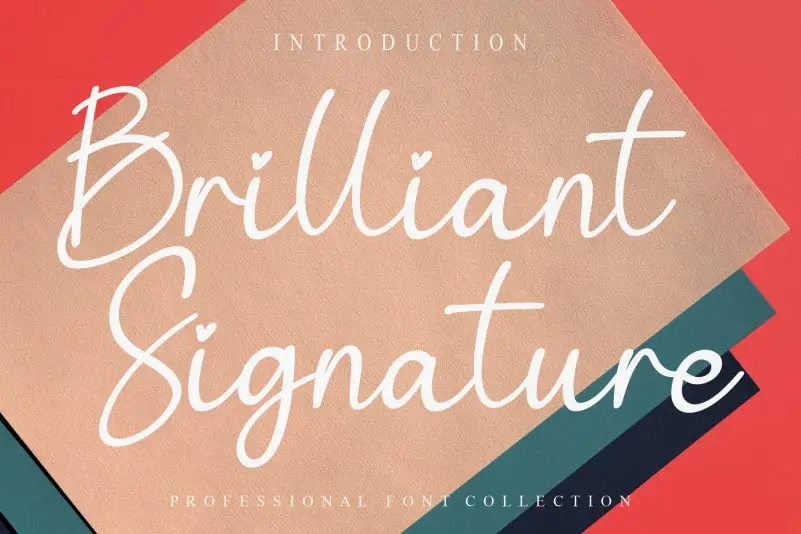
Brilliant Signature Script Font – Download Grátis
Aqui está uma descrição em português do Brasil para a página de download da fonte ‘Brilliant Signature Script Font’, mantendo o tom informativo e convidativo: Descubra uma experiência única com a fonte ‘Brilliant Signature Script Font’. Especialmente criada para quem valoriza personalidade, essa fonte é perfeita para criar mensagens de impacto. Sua elegância e delicadeza transmitem um toque pessoal, ideal para criação de nomes de empresas ou marca, assinaturas exclusivas ou qualquer projeto que necessite de uma escrita autêntica e única. Com a fonte ‘Brilliant Signature Script Font’, suas ideias ganham vida. Ela oferece um grau impressionante de detalhes em cada caractere, criando um estilo inconfundível e de alta qualidade. Seja para textos corporativos ou cartas personalizadas, sua escrita transmite autenticidade e confiança. Ideal para designers gráficos que buscam uma fonte elegante e versátil. Descubra por si mesmo a experiência que essa fonte oferece – ela irradia profissionalismo sem ser previsível, oferecendo aos criadores um recurso de gravação perfeito para qualquer projeto.